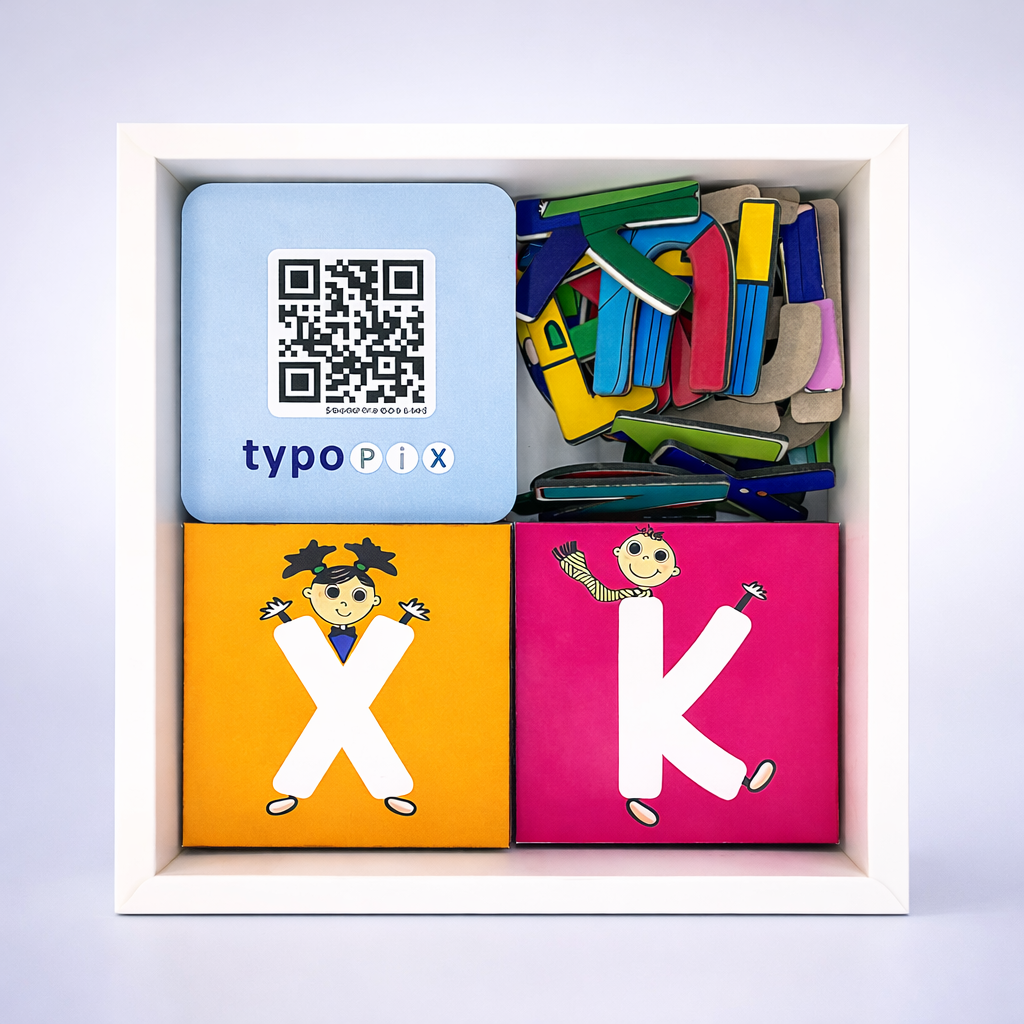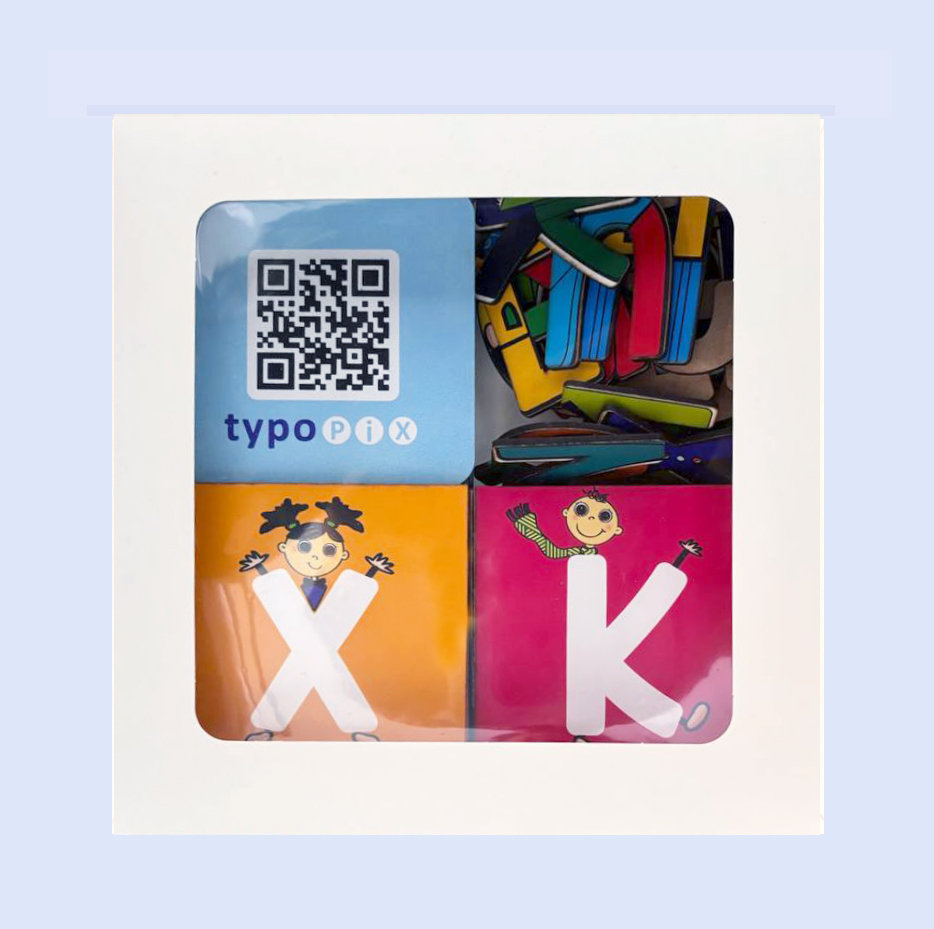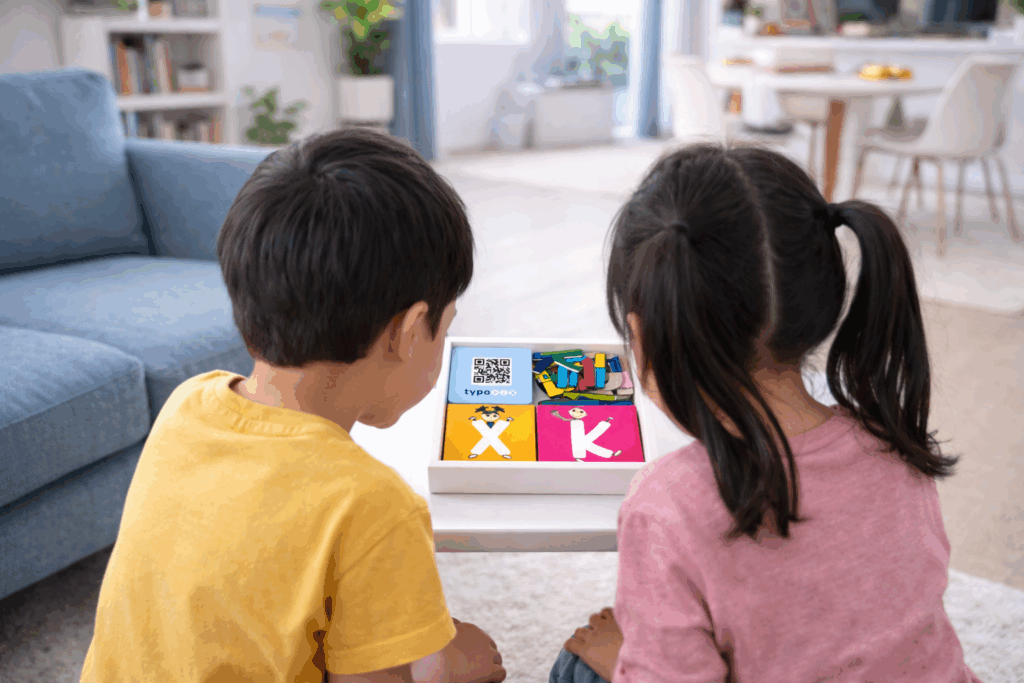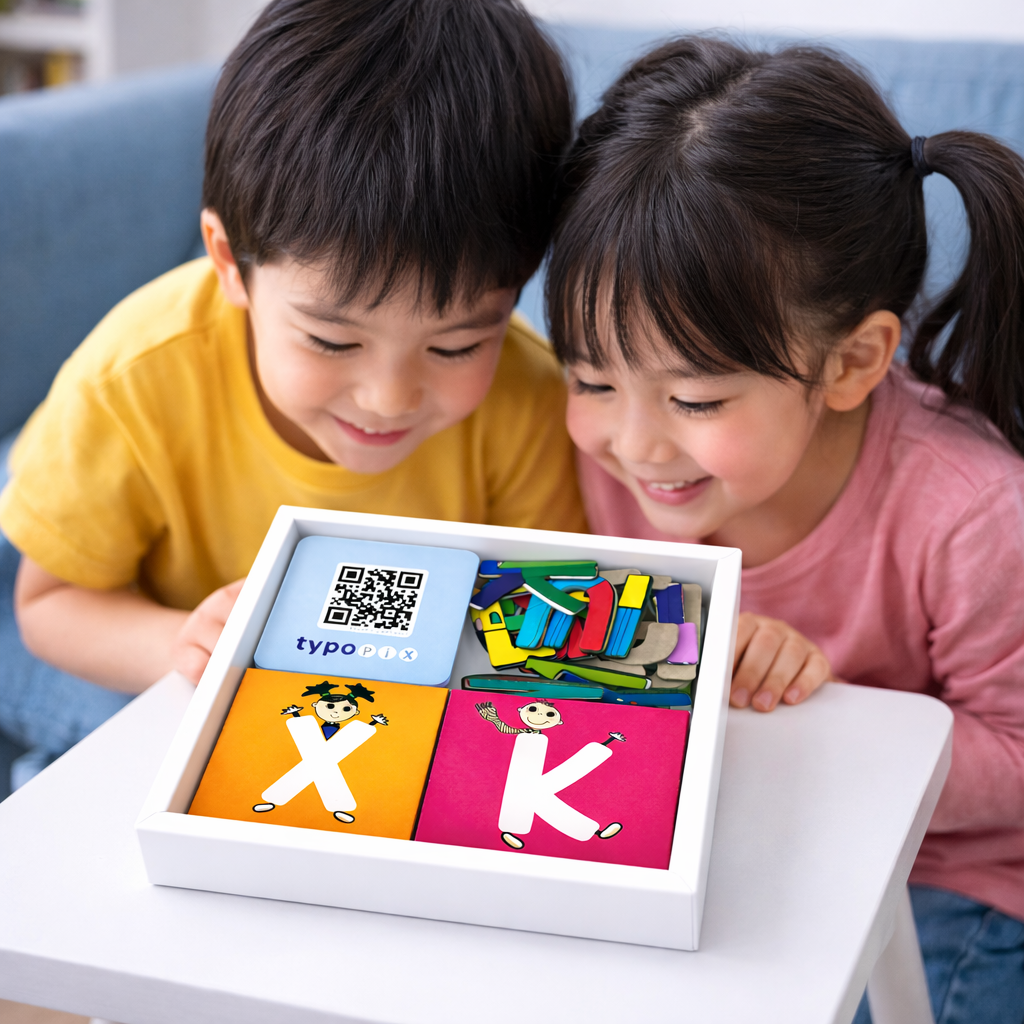
حروف الفبای مگنتی شخصیتدار – یادگیری با دو دوست خیالی!
این مجموعهی جذاب، تجربهای کاملاً متفاوت از آموزش الفبا به کودک شماست.
در هر کارت چوبی ۱۰×۱۰ سانتیمتری، نیمتنه یا بخشی از بدن یکی از دو شخصیت مهربان مجموعه (پسر یا دختر) نشان داده شده—اما بدن شخصیت کامل نیست! بخش اصلی بدن او همان حرف انگلیسی است که به شکل یک تکهی جداگانه و مگنتی طراحی شده.
کودک برای کاملکردن شخصیت، باید حرف درست را پیدا کند، لمس کند، فرم آن را بشناسد و سپس آن را سر جای خودش روی کارت بچسباند. این روند جذاب باعث میشود یادگیری حروف کاملاً بازیمحور، حسی و لذتبخش انجام شود.
⭐ کودک چطور با محصول کار میکند؟
- آشنایی با شخصیتها
کودک ابتدا یکی از دو شخصیت (پسر یا دختر) را انتخاب میکند و برایشان یک اسم دلخواه میگذارد.
این ارتباط ایجادشده، یادگیری را شخصی و احساسی میکند. - دیدن بدن ناقص شخصیت
روی هر کارت چوبی، بخشی از بدن شخصیت نمایش داده شده و قسمت اصلی بدن، سفید و خالی است. - پیدا کردن حرف درست
کودک بین تکههای مگنتی، حرف موردنظر را یافته و آن را در دست میگیرد.
جنس مگنتی و برش دقیق حروف باعث میشود کودک بتواند با لمس، فرم و جهت حرف را راحتتر تشخیص دهد. - تکمیل شخصیت
کودک حرف را روی جای خالی در کارت میگذارد تا بدن شخصیت کامل شود.
چون تکهی حرف مگنتی است، بلافاصله روی کارت چوبی میچسبد و یک تصویر کامل و جذاب شکل میگیرد. - شناخت و تکرار
با هر حرف:- شکل حرف در ذهن تثبیت میشود
- صدا و نام آن راحتتر یاد گرفته میشود
- حافظهی دیداری و لمسی تقویت میشود
- کودک حس موفقیت و کاملکردن کاراکترش را تجربه میکند
برای کودکان ۳ تا ۷ سال—مناسب برای:
- یادگیری حروف الفبای انگلیسی
- تقویت مهارتهای حل مسئله
- هماهنگی چشم و دست
- تشخیص شکل و جهت حروف
- رشد خلاقیت و نقشآفرینی
⭐ چرا این مجموعه خاص و متفاوت است؟
- شخصیتمحور بودن (Naming System)
کودک خودش به شخصیتها اسم میدهد و این باعث میشود کاملاً با آنها ارتباط بگیرد و انگیزه بیشتری برای ادامه بازی داشته باشد. - لمسی + دیداری + بازیمحور
ترکیب لمس حروف، تشخیص فرم، و کاملکردن تصویر، یادگیری را چند برابر مؤثرتر میکند. - قطعات چوبی با دوام + چاپ باکیفیت
کارتها ۱۰×۱۰ هستند، ضخیم، مقاوم و مناسب دستهای کوچک کودک. - حرفها قابلیت جابهجایی دارند
کودک میتواند چند بار امتحان کند، جای درست را پیدا کند و ارزش یادگیری مستقل را تجربه کند. - طراحی رنگی و جذاب
لباس شخصیتها روی خود حروف طراحی شده، که باعث میشود شکل حرف در ذهن ماندگارتر و جذابتر شود. - ایمن و مناسب برای کودکان
لبهها گرد و چاپ بدون مواد مضر.